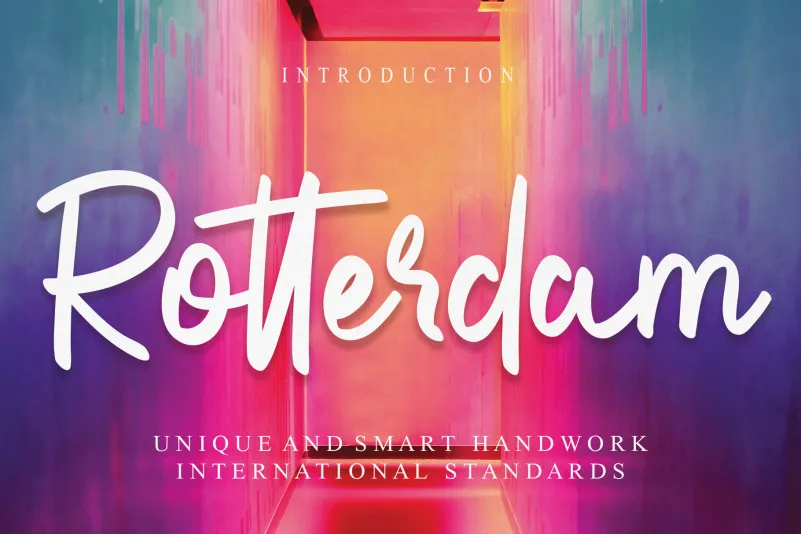
A fonte Rotterdam Brush é uma criação singular, projetada para oferecer aos designers uma maneira única e criativa de expressar ideias. Seu design naturalmente fluido e bem-balanced, combina elementos tanto do script quanto do gráfico, o que a torna uma opção ideal para ambientes onde desejas transmitir profunda sutileza e exuberância visual. Com sua tipografia em brushed style, Rotterdam Brush traz um toque de brilho ao seu design digital. Este estilo especial permite uma expressão mais pessoal e emocional da mensagem que está sendo comunicada, tornando-a perfeita para aplicações em anúncios publicitários, logotipos ou qualquer outro projeto onde você deseja colocar sua marca de maneira única. Essa fonte foi projetada pelo designer creativeletter. Seu design fluido e arredondado proporciona uma experiência visual atraente, que é perfeitamente adaptada para os produtos do seu site. Para designers que valorizam não apenas a funcionalidade da fonte, mas também sua capacidade de trazer vida e personalidade aos seus designs digitais, Rotterdam Brush é uma escolha inteligente.